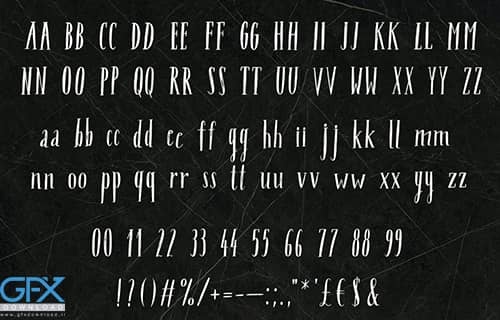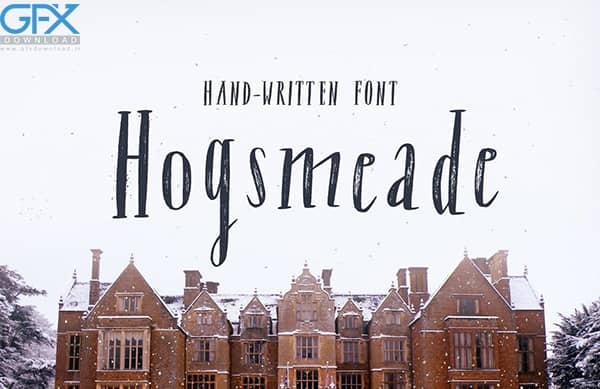
این فونت با سبک متفاوتی که با دست نوشته شده و بافت زیبای حروف به شما کمک می کند تا سرصفحه ها ، لوگوها و سایر تایپوگرافی ها عجیب و غریب و با ظاهر قدیمی به نظر برسند. دانلود فونت Hogsmeade برای طراحی آرم ، شبکه های اجتماعی ، عنوان فیلم ، عنوان کتاب ، یک متن کوتاه حتی یک نامه طولانی مناسب است.